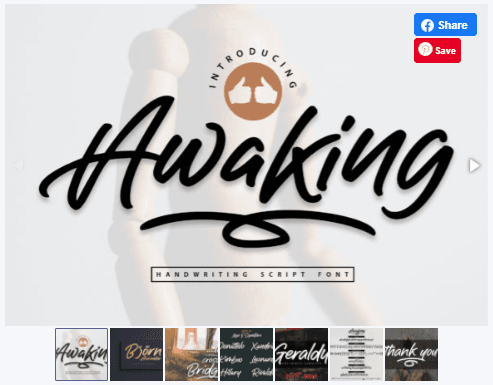
Awaking Font
Awaking - восхитительный рукописный шрифт. Он со вкусом смотрится в любом городском или повседневном дизайне, который требует рукописных штрихов. Этот шрифт имеет кодировку PUA, что означает, что вы можете легко получить доступ ко всем глифам и росчеркам!